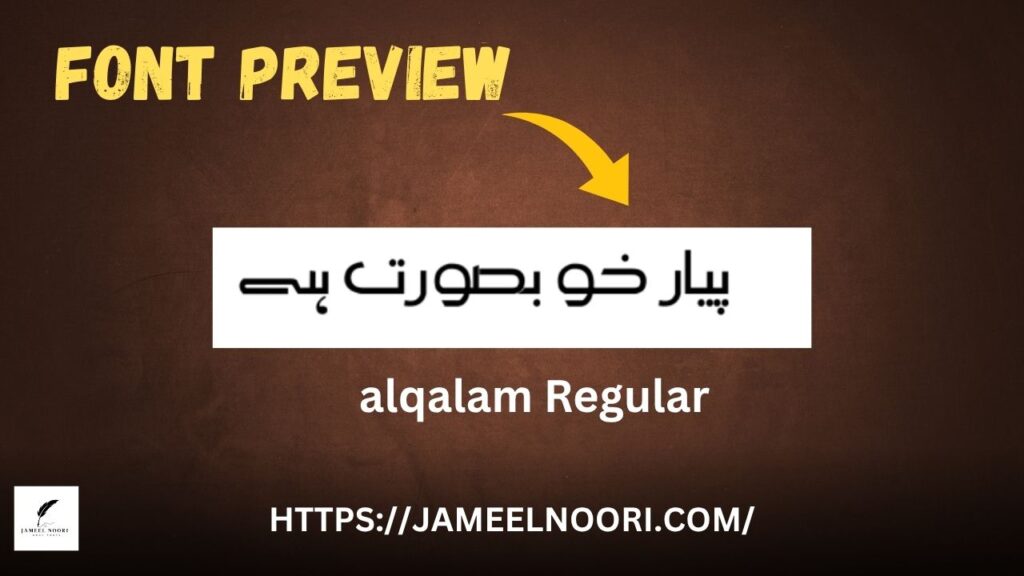
Introduction – AlQalam Regular Urdu Font
Features of AlQalam Regular Urdu Font
- ✅ Highly readable Urdu Nastaliq style
Use Cases – Kin Cheezon Mein Font Ka Istemaal Karein?
- Quranic text likhne ke liye
- Naat, poetry aur Urdu Islamic quotes ke liye
- Urdu blog thumbnails
- Urdu typing practice
- Social media Islamic content design
Font Ki Uniqueness – Yeh Font Itna Popular Kyun Hai?
- Is font ka smooth Nastaliq layout isay perfect banata hai Quranic aur religious Urdu content ke liye.
✅ Conclusion
Kya yeh Quranic calligraphy ke liye best font hai?
Jee bilkul, yeh font specially Quranic aur Islamic design ke liye behtareen hai.